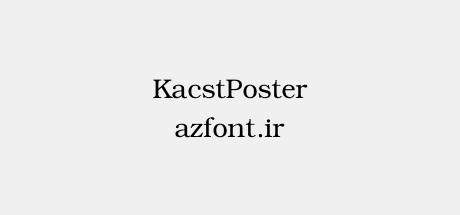
KacstPoster
فونت زیبای رایگان KacstPoster
قلم زیبای KacstPoster از سری قلم های بسیار زیبا برای تایپوگرافی و لوگو تایپ می باشد.این قلم در وزن KacstPoster و توسط Regenerated by Nadim Shaikli طراحی و منتشر شده است.